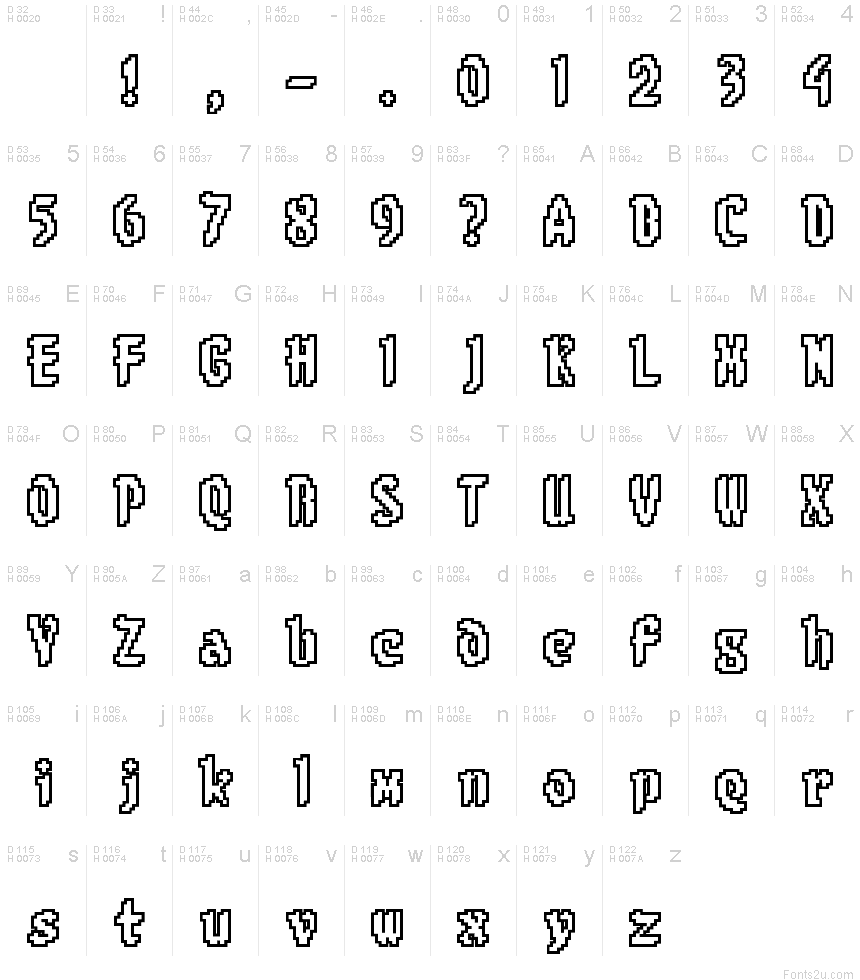
8-bit Limit O to zachwycający font bitmapowy o wyrazistej, pikselowej estetyce. Jego skondensowany, obrysowany design przywołuje niepowtarzalny urok retro, kojarzący się z klasyczną typografią gier wideo. Kanciaste, geometryczne litery tego kroju płynnie łączą precyzję pixel artu z odważnym, przyciągającym wzrok stylem wizualnym.
Wszechstronność fontu 8-bit Limit O sprawia, że jest on atrakcyjnym wyborem dla wielu projektów graficznych – od interfejsów gier wideo i materiałów promocyjnych, po branding oraz opakowania w stylu vintage. Jego unikalny charakter pozwala wyeksponować treść, nadając każdemu projektowi nostalgiczną, a zarazem współczesną formę.
8-bit Limit O (BRK)